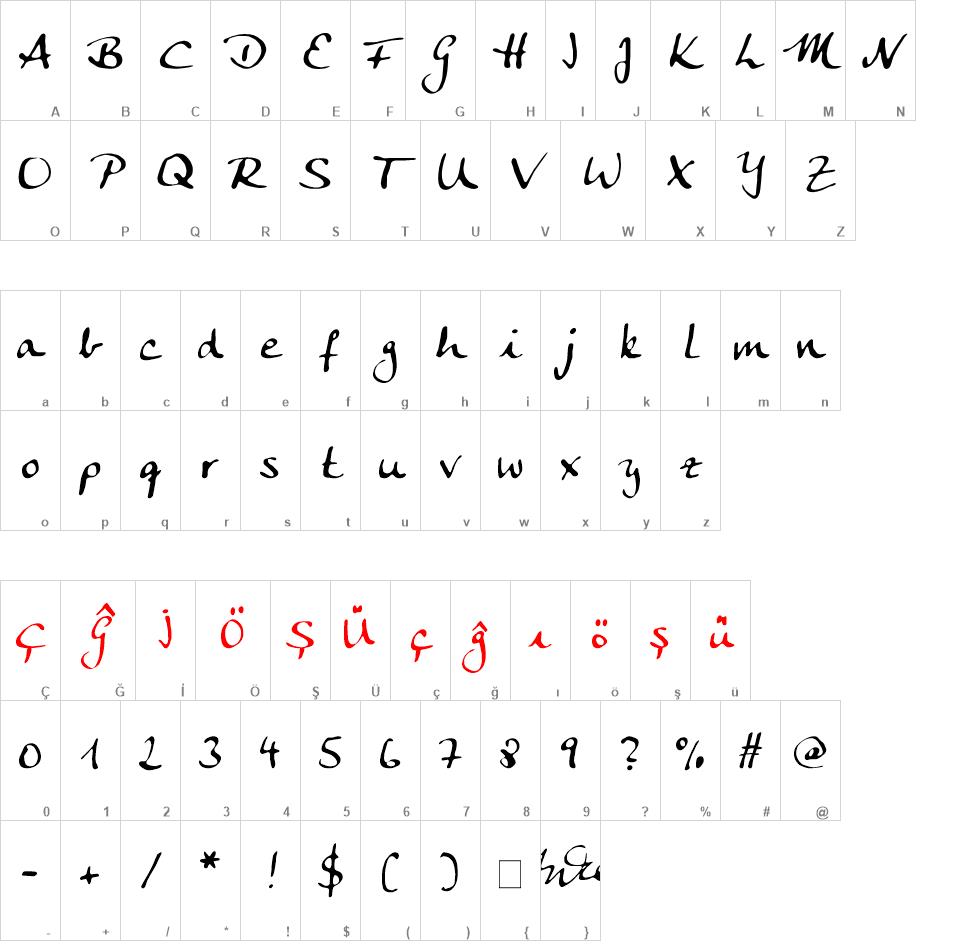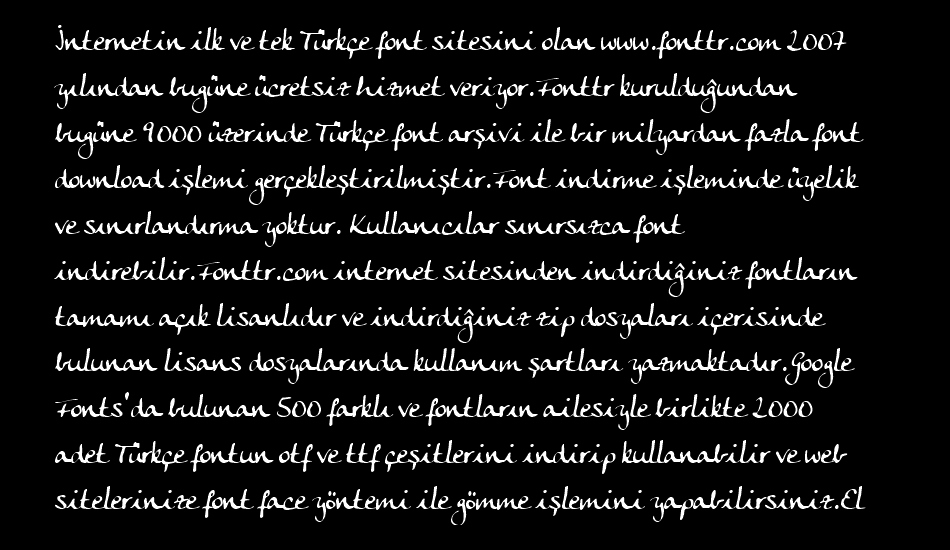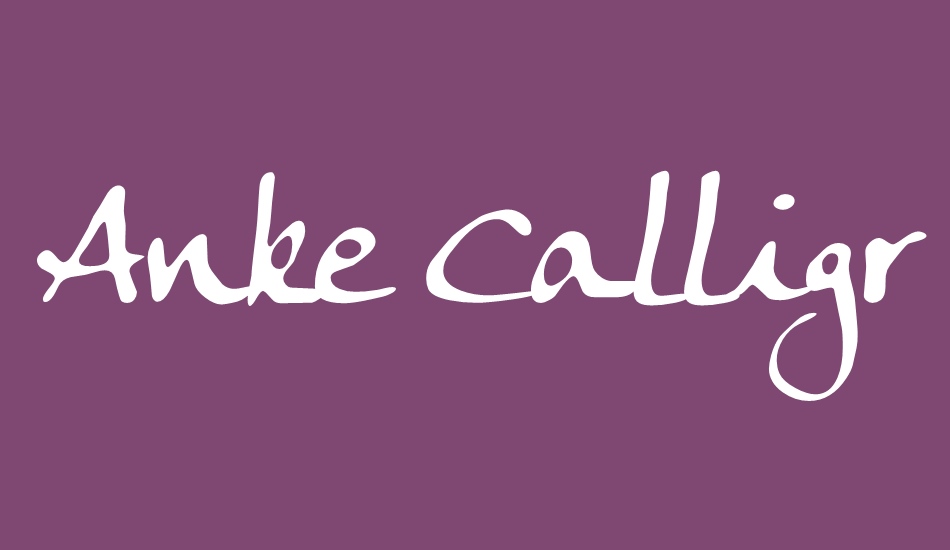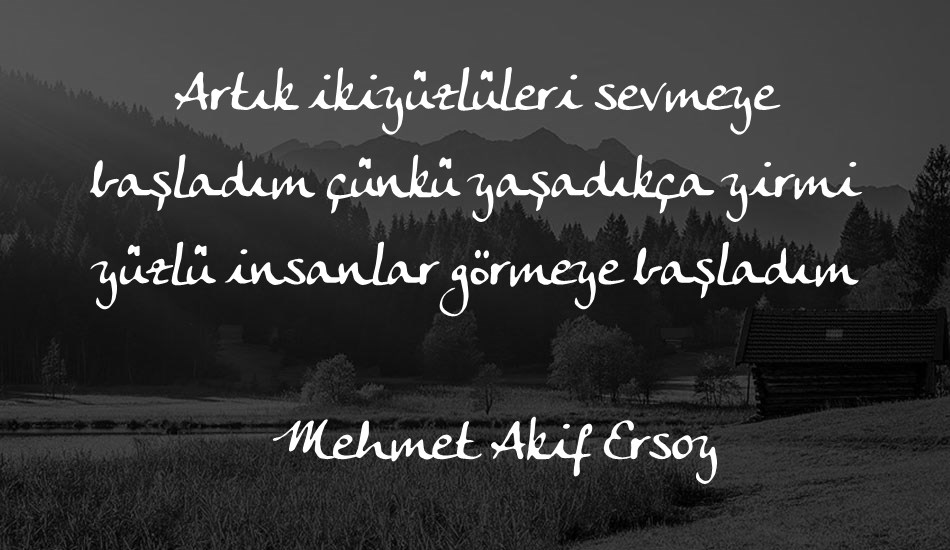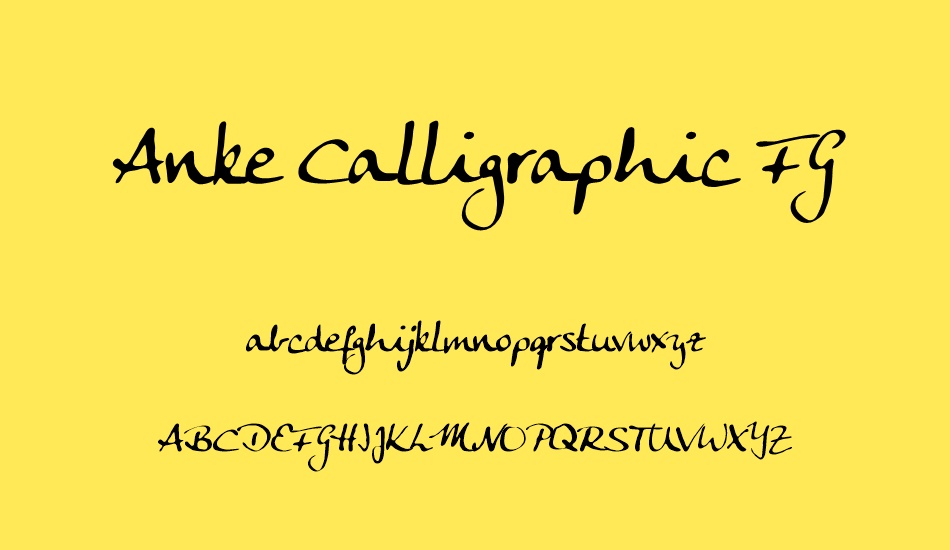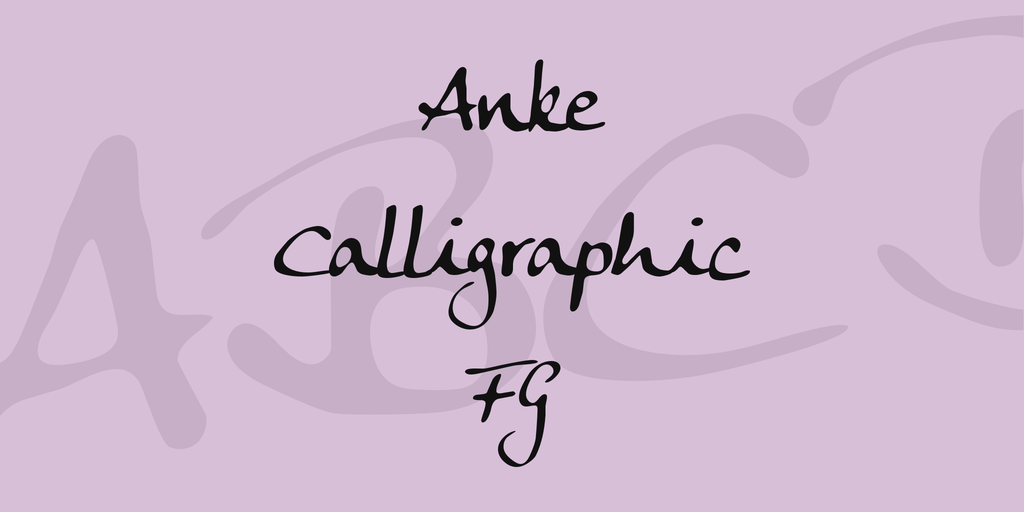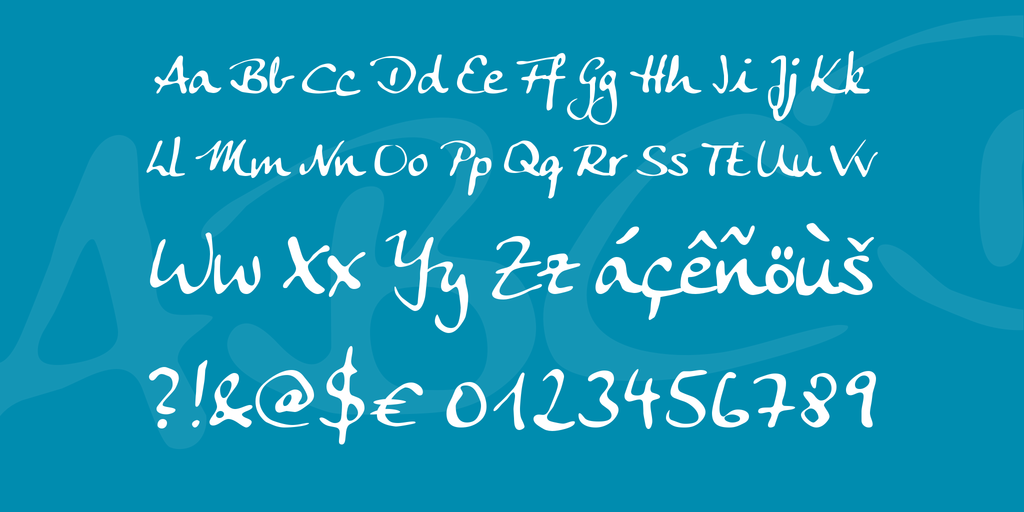
Anke Calligraphic FG font
Orijinal olarak Anke Arnold, www.anke-art.de tarafından hazırlanan bu elyazısı yazı tipi, uluslararası karakterlerle güçlendirildi ve Fontgrube AH tarafından dikey ayarlamaların yanı sıra aralıklarla yeniden düzenlendi, daha sorunsuz çalışması için 100 kern çift eklendi, bu nedenle karakter aralığına sahip olduğunuzdan emin olun. Sözcük işlemcinizde veya DTP programınızda açılır. Yazı tipi, OpenType özellikleri için destek gerektirmeden, kaligrafik el feneri ile rahat el yazısını taklit etmeye çalışır. Günlük kullanıcılara yöneliktir ancak profesyonel bir bağlamda ücretsiz olarak kullanılabilir.